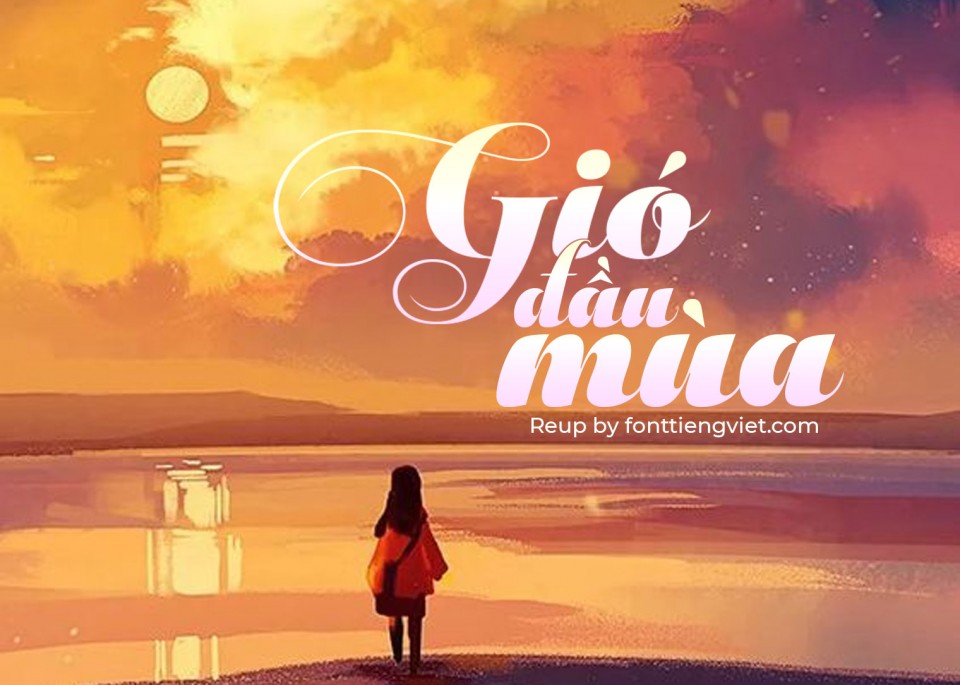
Font việt hóa HLT Aparo
Giới thiệu về bộ Font việt hóa HLT Aparo độc đáo
Trong thế giới đồ họa hiện đại, việc tìm kiếm một mẫu Font Miễn Phí có phong cách cổ điển xen lẫn nét thanh lịch là điều vô cùng cần thiết. Font việt hóa HLT Aparo chính là lựa chọn hoàn hảo dành cho những ai yêu thích sự mềm mại của các đường nét viết tay. Đây là bộ phông chữ thuộc phong cách Script, mang đến cảm giác uyển chuyển và chuyên nghiệp cho mọi dự án sáng tạo. Với việc được việt hóa hoàn chỉnh, người dùng tại Việt Nam có thể dễ dàng sử dụng các ký tự đặc trưng mà không lo bị lỗi font hay thiếu dấu chữ cái.
Tại sao nên sử dụng Font việt hóa HLT Aparo trong học đường?
Đối với các bạn học sinh và giáo viên, việc trình bày các bài thuyết trình hay thiết kế báo tường đòi hỏi sự rõ ràng nhưng vẫn phải bắt mắt. Font việt hóa HLT Aparo cung cấp hệ thống ký tự đồng nhất, giúp các tiêu đề bài giảng trở nên nổi bật hơn. Đặc biệt, bộ chữ này rất phù hợp để thiết kế thiệp mời, bằng khen hoặc các tài liệu giáo dục mang tính trang trọng. Sự kết hợp giữa nét thanh và nét đậm giúp văn bản có chiều sâu, tạo ấn tượng mạnh mẽ với người xem ngay từ cái nhìn đầu tiên.
Cách ứng dụng Font việt hóa HLT Aparo hiệu quả nhất